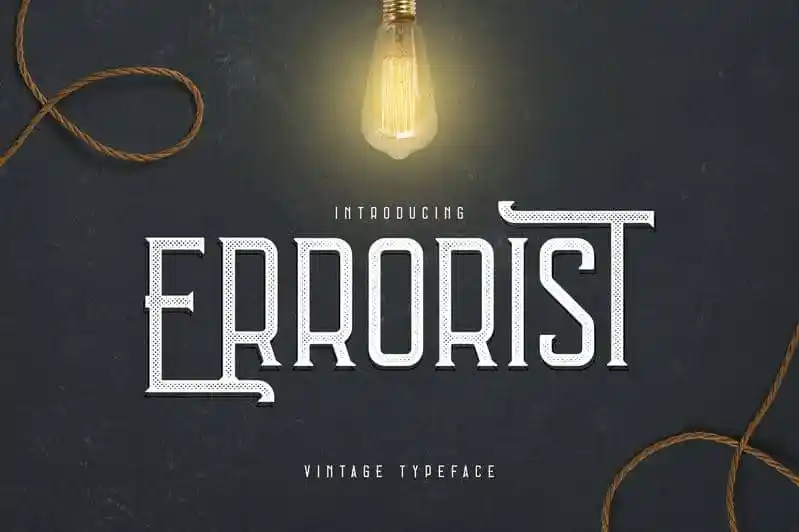
A Fonte Vintage Errorist oferece uma experiência única para designers buscando inspiração nostálgica sem perder a praticidade moderna. Este tipoográfico foi criado com três estilos distintos, garantindo uma variedade que atende diferentes demandas gráficas. Além disso, sua disponibilidade em vários idiomas reforça seu potencial de uso em diversos projetos internacionais. Com milhares de opções alternativas de letras e um layout cuidadosamente pensado, a Errorist se torna uma fonte ideal para quem busca ambas as características do vintage e da modernidade contemporânea. Ideal tanto para trabalhos em linguagens estrangeiras quanto para projetos que valorizam o passado das letras typográficas, este é um ótimo recurso para designers buscando uma solução versátil e elegante. Através de seu design minimalista mas contendo detalhes meticulosamente elaborados, a Errorist também oferece uma qualidade superior em impressões digitais e papel. Este fator torna-a particularmente adequada para criações que exigem alta resolução, como materiais publicitários ou infográficos profissionais. No entanto, é importante notar que o designer vp_creative_shop criou esta fonte com uma forte aposta em sua autenticidade vintage enquanto preservando a estética moderna. Essa mistura de elementos permite ao usuário manter um toque nostálgico sem comprometer a funcionalidade e qualidade atuais.